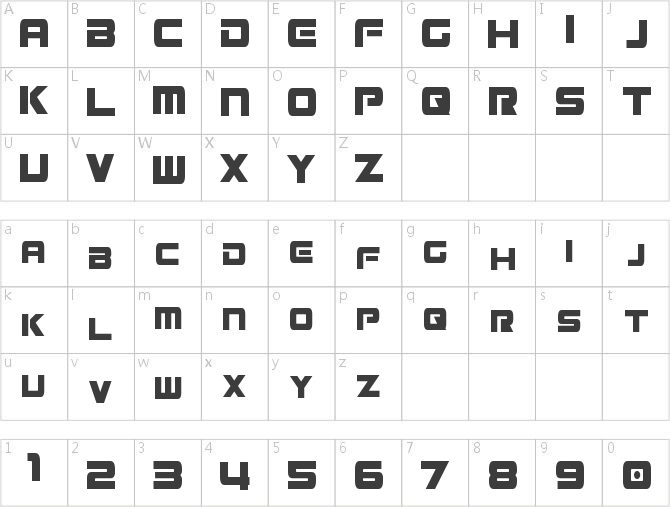
Mission-GT-R-Condensed 詳情頁
字體名稱: Mission
Mission-GT-R-Condensed
Mission-GT-R-Condensed介紹
Mission-GT-R-Condensed字體字庫是一款讓人賞心悅目、百看不厭的英文字體,適合各類廣告和產品包裝設計應用,字體大小0.02MB,格式為ttf字體,上傳用戶是多喝燙水,作者/版權方為未知